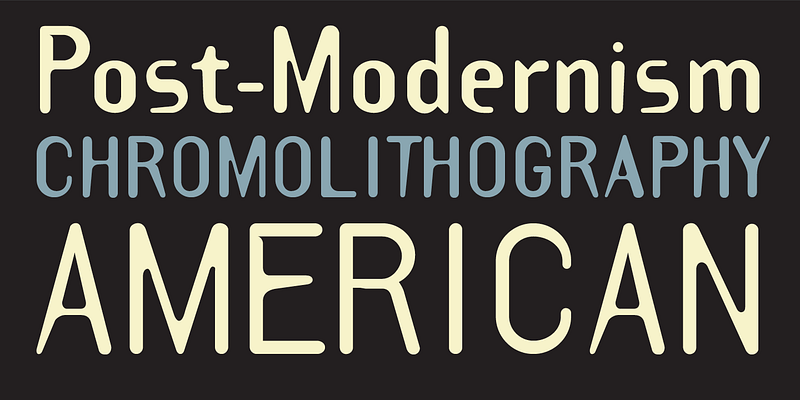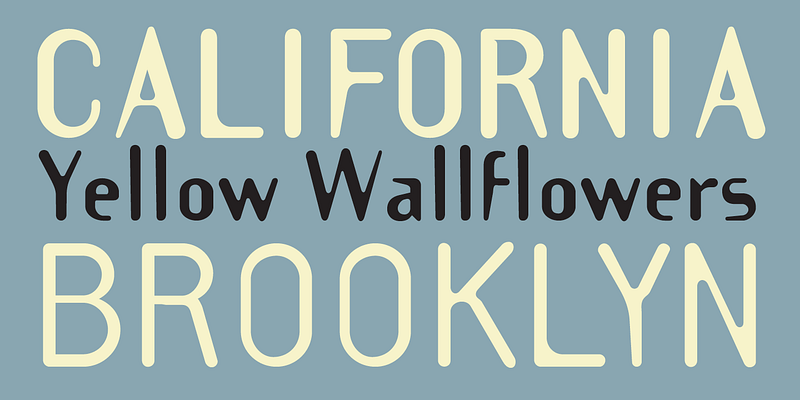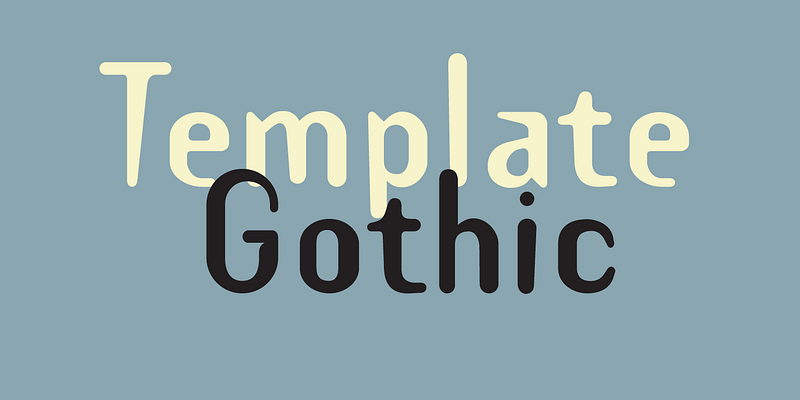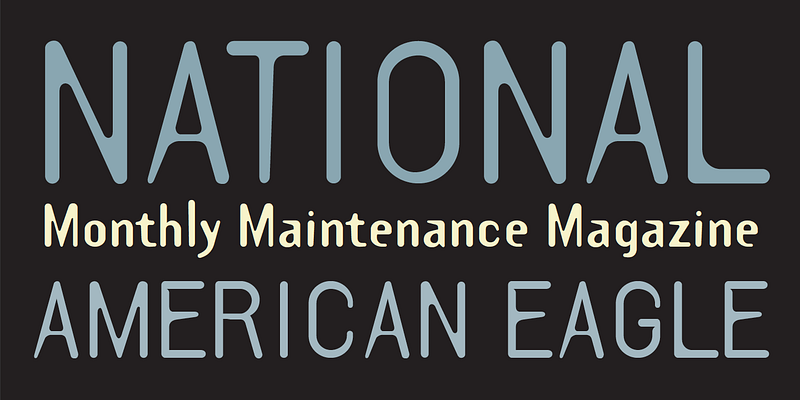
Template Gothic wurde von Deck entworfen, während er in den späten 80er und frühen 90er Jahren an der CalArts in Valencia, Kalifornien, Design studierte. CalArts war eine der ersten Designschulen, die mit Schriftdesign am Computer experimentierte. Unter der Leitung der Dozenten Jeffery Keedy und Ed Fella brachte das Programm eine Fülle von Schriftentwürfen hervor.
Template Gothic ist ein wichtiger Meilenstein in der Geschichte der digitalen Schriftarten, nicht nur wegen ihrer Popularität, sondern auch wegen der einzigartigen Stimme des Designers und der volkstümlichen Quelle, die er als Inspiration nutzte - ein Schild, das in seinem Waschsalon in der Nachbarschaft angebracht war.
Template Gothic war Ende der 1990er Jahre allgegenwärtig und repräsentierte die Ästhetik der Unvollkommenheit, die von einigen Designern in der Postmoderne geliebt wurde. Deck, wie auch andere Schriftgestalter dieser Zeit, sprach von seinem Wunsch, die Perfektion der modernistischen Buchstabenformen aufzugeben: „Ich war inspiriert, eine Schrift zu entwerfen, die so aussieht, als hätte sie die Verzerrungen der fotomechanischen Reproduktion erlitten.“ Seine Schrift spiegelt „wahrhaftig die unvollkommene Sprache einer unvollkommenen Welt wider, die von unvollkommenen Wesen bewohnt wird.“
Im Jahr 2011 war Template Gothic eine von 23 digitalen Schriften, die in die ständige Architektur- und Designsammlung des Museum of Modern Art in New York aufgenommen wurden.